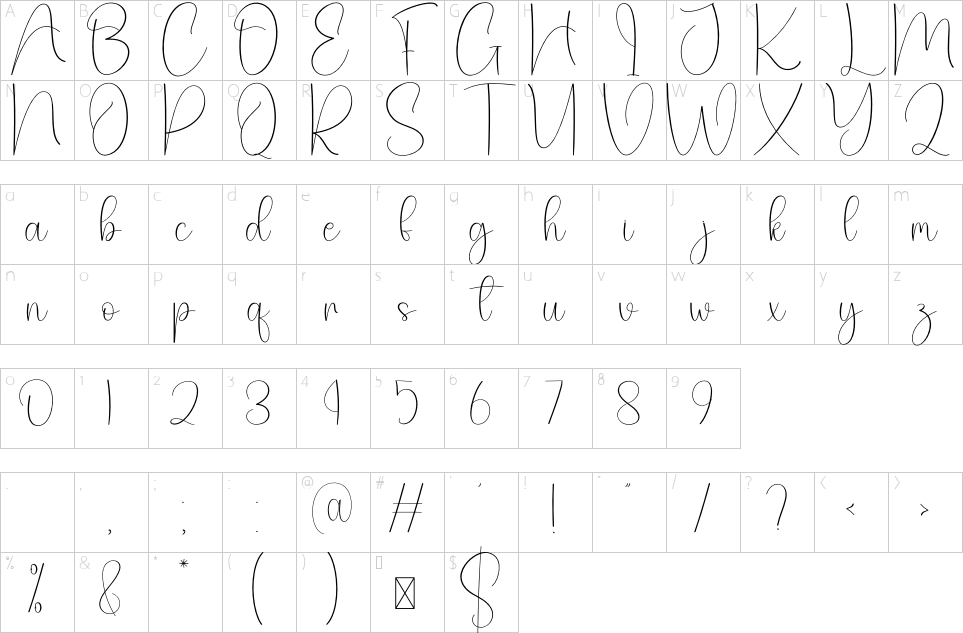
Descubra a fonte ‘Donkey Font’ para seu projeto criativo! Esta elegante fonte foi criada por scratchones e é uma ótima opção para aqueles que buscam um estilo descontraído sem perder a qualidade. Com design minimalista, Donkey font oferece um tom de humor leve que certamente irá enriquecer qualquer projeto gráfico ou marca visual. Sua simplicidade e agilidade tornam-na perfeita tanto para títulos quanto para textos mais detalhados. Donkey Font é uma opção gratuita de alta qualidade, disponível tanto em Windows como Mac. Com 469 downloads já realizados, você pode ter certeza de que esta font está ganhando popularidade entre os designers digitais. Não espere mais e descubra a versatilidade desta font exclusiva para seu próximo projeto!